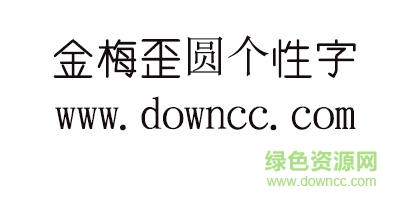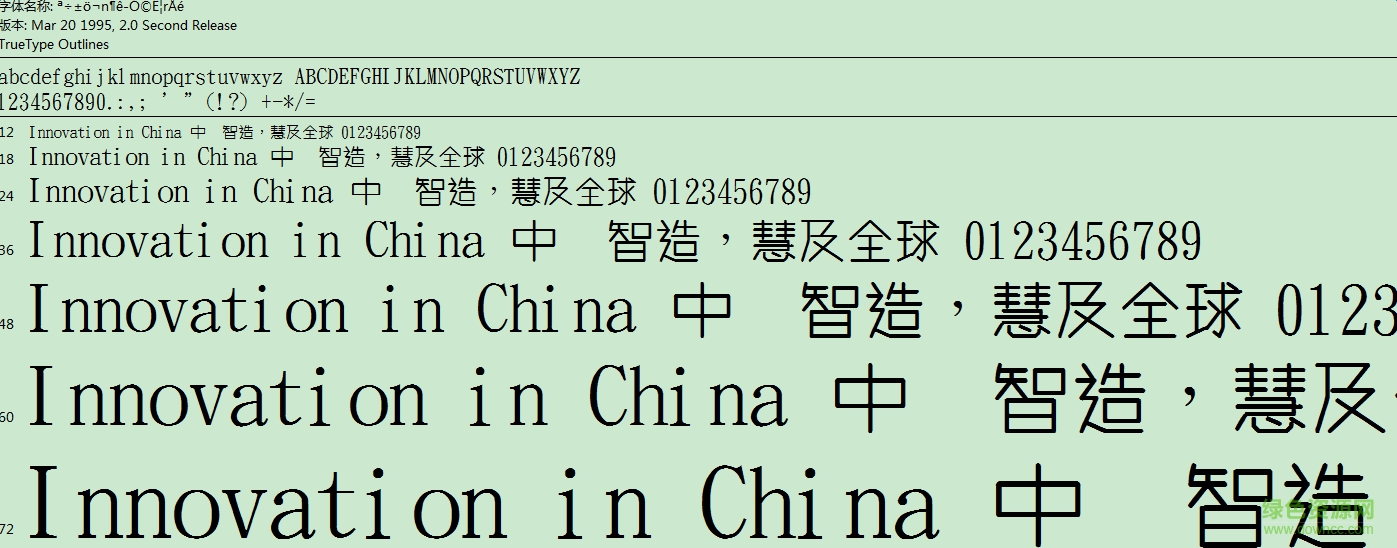
金梅歪圓個(gè)性字體是一款免費(fèi)的金梅繁寫字體,字形如其名,書寫的字體非常的有特點(diǎn),可以用在藝術(shù)行業(yè)設(shè)計(jì)使用!有需要的朋友可以來(lái)綠色資源網(wǎng)免費(fèi)下載哦,還有更多好看的金梅字體等你來(lái)發(fā)現(xiàn)!